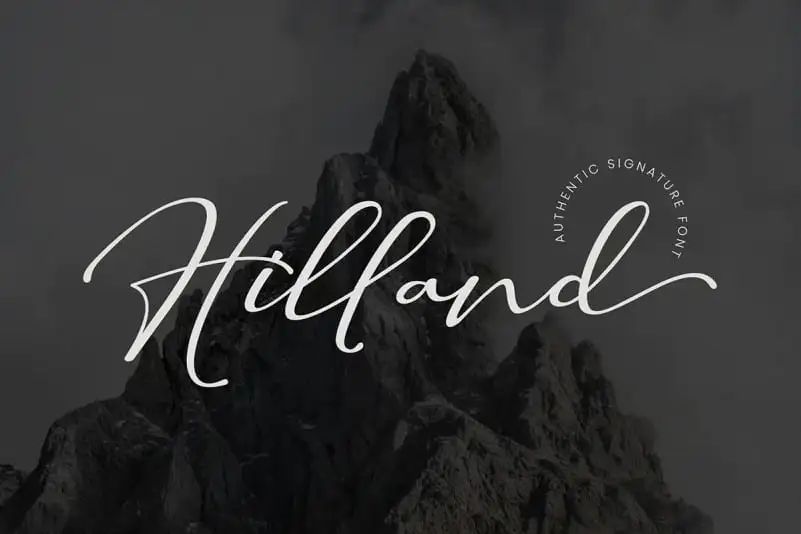
Hilland Script Font – Download Grátis
A fonte ‘Hilland Script Font’ é uma escolha perfeita para qualquer projeto que exija elegância e charme. Desenhada pela Beautypes Studio, esta fonte escrita a mão possui um tom robusto, oferecendo um brilho único e atemporal aos seus projetos. Ideal para cartões de presentes, materiais de marca, cartazes de Natal, cards de negócios, frases motivacionais ou quaisquer outros designs que exigem um toque sofisticado e moderno. Com uma linha pontual que dá vida a cada letra, o ‘Hilland Script Font’ cria um design fresco e atual. Seu aspecto elegante faz dele perfeito para incorporar em cartões de aniversário, revistas ou até mesmo em ilustrações digitais. Este é também um excelente escolha para criar materiais de branding profissional que precisam se destacar. Essa fonte escrita a mão traz ao seu design uma graça ímpar e um toque pessoal. Com a ‘Hilland Script Font’ na sua arsenal, você pode transformar qualquer projeto em um trabalho final único e memorável. Com certeza será um recurso invaluable para designers que desejam criar designs autênticos com um toque sofisticado.